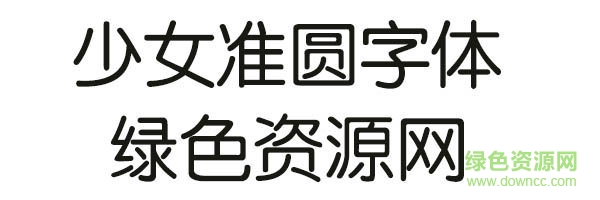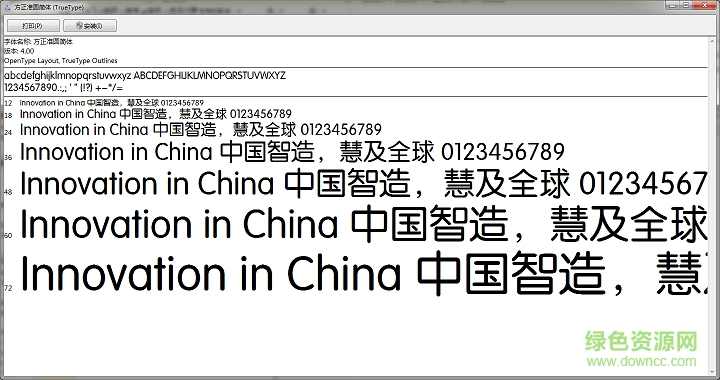
少女準(zhǔn)圓字體是一款比較熱門的手機(jī)字體,在電腦端即為方正準(zhǔn)圓簡體,綠色資源網(wǎng)帶來的為少女準(zhǔn)圓字體ttf版,喜歡的朋友,趕快到綠色資源網(wǎng)拿走吧!
少女準(zhǔn)圓字體是猶如少女一般清新可愛的字體,是現(xiàn)在超多用戶選擇的字體之一,形態(tài)優(yōu)美好看